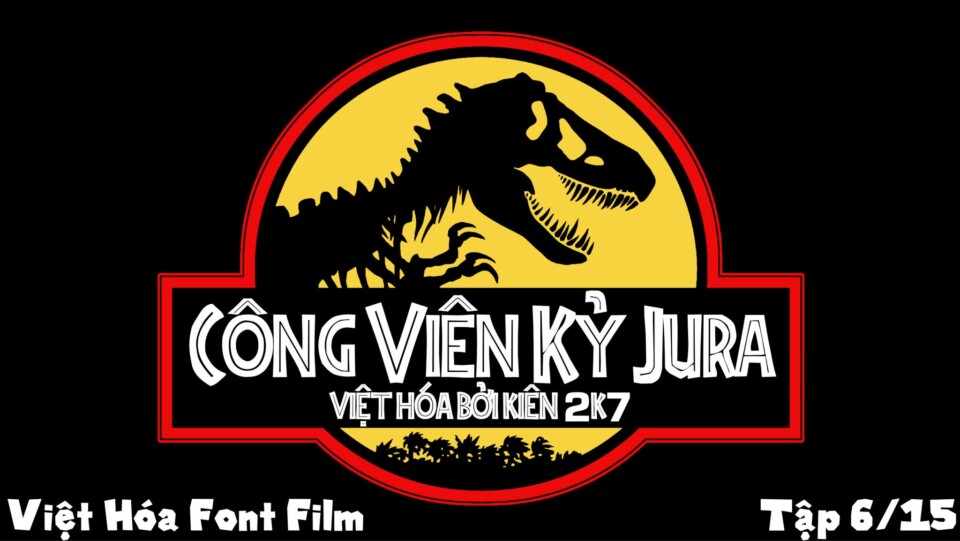
Font Việt hóa phim Jurassic Park – KK7-Jurassic Park
Giới thiệu về Font Việt hóa phim Jurassic Park – KK7-Jurassic Park
Chào mừng các bạn đến với thế giới thiết kế đồ họa sáng tạo. Nếu bạn là một người hâm mộ cuồng nhiệt của loạt phim Công viên kỷ Jura, chắc chắn bạn không thể bỏ qua bộ Font Việt hóa phim Jurassic Park – KK7-Jurassic Park. Đây là một bộ Font Miễn Phí được thiết kế dựa trên logo biểu tượng của bộ phim huyền thoại, giúp mang lại phong cách mạnh mẽ, hoang dã và đầy kịch tính cho mọi dự án của bạn. Việc sử dụng font chữ này giúp các bạn học sinh và giáo viên dễ dàng tạo ra các bài thuyết trình hay báo cáo sinh động hơn.
Đặc điểm nổi bật của bộ font KK7-Jurassic Park
Bộ Font Việt hóa phim Jurassic Park – KK7-Jurassic Park sở hữu những đường nét góc cạnh, mô phỏng hoàn hảo phong cách của thời kỳ tiền sử. Phiên bản Việt hóa này đã được tối ưu hóa hoàn toàn để hiển thị chính xác các dấu tiếng Việt mà không bị lỗi font hay mất chữ. Điều này cực kỳ quan trọng đối với các nhà sáng tạo nội dung tại Việt Nam khi muốn duy trì tính thẩm mỹ mà vẫn đảm bảo nội dung rõ ràng, dễ đọc.
Ứng dụng Font Việt hóa phim Jurassic Park – KK7-Jurassic Park trong học tập
Trong môi trường giáo dục, việc sử dụng font chữ độc đáo giúp thu hút sự chú ý của người xem. Bạn có thể dùng font này để làm tiêu đề cho các tờ báo tường, thiết kế thiệp mời sự kiện trường học hoặc làm nổi bật các từ khóa chính trong bài giảng PowerPoint. Sự mạnh mẽ của các ký tự sẽ giúp thông điệp của bạn trở nên quyền lực và khó quên hơn bao giờ hết.
Kết luận về bộ font thiết kế đặc biệt